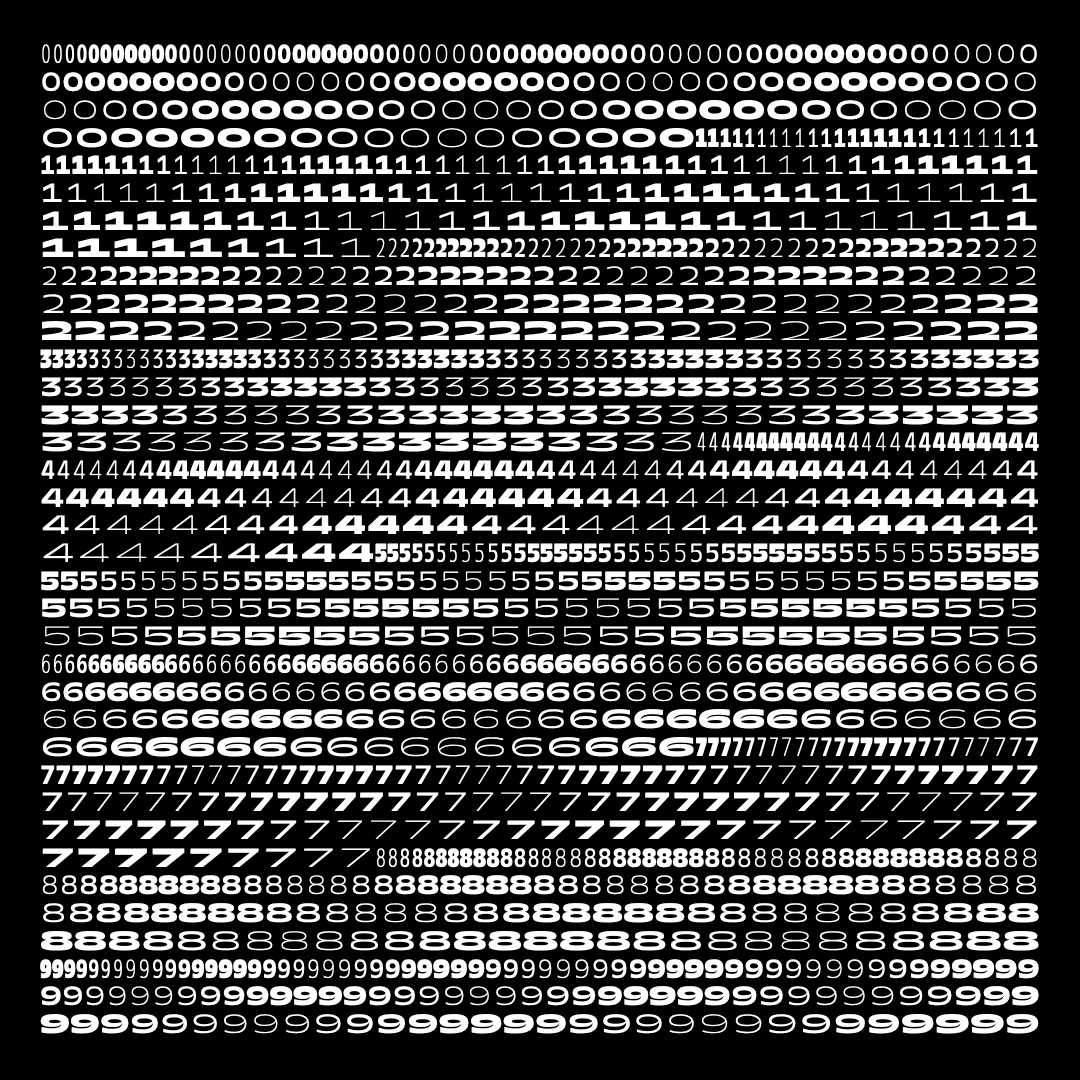
Variable Font: Fließende Anpassungen in einem Absatz; InDesign
ich experimentiere zur Zeit mit variable Fonts in InDesign. Stellt euch dabei folgende Situation vor: Der Absatz des Textes beginnt mit einem schmalen Schriftschnitt. Im Verlauf des Textes fängt die Schrift langsam an immer stärker zu werden, bis sie am Ende der Seite extra-fett wird. Ist es möglich diesen Effekt im InDesign mit variablen Fonts zu erzeugen? Gibt es evtl. ein PlugIn, mit dem man die verschiedenen Zustände des Schriftart fließend im Text ansteuern kann?
hier gibt’s jede menge begabtere grep-spezialisten als mich, aber ich vermute, in dem speziellen fall wird man um viel handarbeit nicht herumkommen.
Ganz allgemein gesprochen: Das ist eher ein Fall für Scripting, nicht für GREP.
GREP: Da praktisch jeder Buchstabe eine Nuance verändert werden soll, müssten erst mal entsprechend viele Zeichenformate angelegt werden, die dann Buchstabe für Buchstabe (automatisch) zugewiesen würden. Das ist immer noch Arbeit, und jede Änderung 1x die selbe Arbeit erneut.
Script in der Theorie
1. Buchstabenzahl in der Markierung / im Absatz ermitteln  (z.B. 500 Zeichen)
2. Minimal- und Maximalwert der variablen Achse des Fonts ermitteln (z.B. von 0 bis 100)
3. Die Anzahl der Buchstaben auf von Minimal- bis Maximalwert verteilen, also die nötige "Schrittweite" ermitteln (z.B: +0,2)
4. Buchstabe für Buchstabe durchgehen lassen, und dabei den Formatierungs-Achsenwert jeweils um eine Schrittweite erhöhen (0,2 0,4 0,6 0,8 1,0 ... 99,6  99,8  100)
In der Praxis ist das keine leichte Nuss zu knacken ...
• zum einen müssen die passenden Befehle für Zeichenzählen und vor allem die Achsenwerte der Fonts gefunden werden, da die recht neu sind ist wahrscheinlich noch wenig vorhanden (im Zweifel: vertiefe dich in der Javascript-Variante der Indesign-Scripts, nicht Applescript oder VBscript – das ist allgemeingültig und soweit ich das sehe besser dokumentiert).
• zum anderen: das Ergebnis könnte gerade bei kurzen Texten ungleichmäßig ansehen, da die Abstufung natürlich nicht völlig fließend ist, sondern eben in Schritten. Wenn dann die Buchstaben verschieden breit sind (ein m ist dann ja doch 4-5x breiter als ein i) bringt das Unregelmäßigkeit rein.
Eine Lösung dafür wäre, die Buchstabenbreite und die "Gesamttextbreite" zu ermitteln und bei der Schrittweite zu berücksichtigen, aber da wirds mathematisch recht komplex  (einfach nur den erst ermittelten Standard-Schritt erhöhen wenn ein m kommt, geht rechnerisch nicht auf, da die Zahl der ms und is (und aller anderen) ja nicht gleichmäßig verteilt ist).
Das verbesserte Script sähe theoretisch so aus:
1. Gesamtextlänge des Absatzes ermitteln (z.B. 10000 pt)
2. Minimal- und Maximalwert der variablen Achse des Fonts ermitteln (z.B. von 0 bis 100)
3. die "Sub"-Schrittweite pro pt Textlänge ermitteln um von Anfang bis Ende von "0" bis "100" zu kommen (statt wie zuvor pro Buchstabe)
4. Buchstabe für Buchstabe durchgehen lassen, und dabei die Breite dieses einen Buchstabens ermitteln, dem entsprechend viele Sub-Schrittweiten für die Anpassung des Buchstabens anwenden und den Formatierungs-Achsenwert jeweils darum erhöhen (m bekommt z.B: 50 Sub-Schritte, ein i bekommt nur 15, ...).
Das sollte ein gleichmäßigeres Ergebnis erzeugen, mit zwei "Kleinigkeiten":
• "Innerhalb" der Buchstaben ist natürlich kein Werte-Verlauf möglich, das gibt die Technik nicht her. D.h. ein "m" ist am Anfang zu dick, und am Ende zu dünn.
• Auch ist die "Gesamttextlänge" nicht ganz einfach ... wenn das ein guter Font ist, kommt Kerning ins Spiel, das verringert in der Regel die Gesamttextlänge, ist dann aber bei der Messung jeder einzelnen Buchstabenbreite nicht mehr so einfach zu berücksichtigen (es geht mit "Vorschau" auf das nächste Zeichen und Ermittlung des Kernings dazwischen, aber da wirds dann endgültig ... schwierig).
vor 54 Minuten schrieb Sebastian Nagel:
Da praktisch jeder Buchstabe eine Nuance verändert werden soll,
Vielleicht würde es @Jo Nas ja fürs Erste auch schon genügen, in Zeilen »zu denken«? Würde das die Sache nicht erheblich vereinfachen und eventuell möglich machen?
vor 9 Minuten schrieb R::bert:
in Zeilen »zu denken«?
Wäre jetzt auch mein Vorschlag gewesen :nicken:
Das könnte ich mir auch in der Erscheinung besser vorstellen, weil der »Verlauf« nur in eine Richtung ginge. Ansonsten hätte man am Zeilenanfang immer einen Bruch, weil dort der Sprung größer ist als in der Zeile – je nachdem wie groß die einzelnen Sprünge und wie lang die Zeilen sind :-?
Gerade in einer Werbung von Sharp:
9d3f62b4-042d-4d13-8a3b-d85fe3f40afd.gif
Da alterniert jedes Zeichen. Aber muss halt nichts berechnet werden (siehe Beitrag von Sebastian), da einfach nacheinander alle fetten durchlaufen.
@Sebastian Nagel Vielen Dank für die ausführliche Antwort. An die Problemstellung des Kernings habe ich noch garnicht gedacht. In Anbetracht der doch sehr komplexen Umsetzung würde ich eher zur "1-Zeilen-Lösung" von @R::bert tendieren.
@Thomas Kunz super Beispiel! Soähnlich habe ich es mir auch vorgestellt. Kennt ihr evtl. ein Code-Beispiel für ein ähnliches Projekt? Gern auch lösgelöst von InDesign, wenn das einfacher ist.
Vielen Dank für die tolle Hilfe!
@R::bert Gute Idee! Ich habe mich mit dem Designer in Verbindung gesetzt. Wenn er die Lösung für das Problem verrät, poste ich es hier in den Feed.
@TobiW die Software war mir völlig neu. Ziemlich spannende Sache. Das könnte funktionieren. Auf youtube habe ich bereits Beispiele gefunden, die in die richtige Richtung gehen.
ein paar Einwürfe (vom Smartphone aus – edit: nachformatiert )
Zeilenweise (also nur von links nach rechts)
das Prinzip bleibt das gleiche (Stufen auf Zahl der Zeichen / Zeilenlänge verteilen). Der visuelle Effekte ist ein anderer.
Aber: wenn das ein durchgängiger Text ist, also das Ende der Zeile nicht manuell umbricht (Prosa statt Vers), dann verändert sich durch die Formatierung die Zeilenlänge, der Text bricht früher um als in normaler Formatierung, und was ganz rechts fett sein sollte steht jetzt links und sollte dünn sein - spannend ;-) das geht mit Rekursionsschleifen bis eine Balance gefunden ist, aber da möchte ich nicht mal anfangen drüber nachzudenken ...
Bei Durchwanderen des ganzen Absatzes wird zwar der Absatz länger, aber die Zeilen beeinflussen sich nicht gegenseitig. Vielleicht ist das also sogar die einfachere Übung.
Sharp-Beispiel
da haben wir die Vereinfachung, dass die Zahl der Zeichen fixiert ist, die Zahl der Fettgrade fix ist, und dann nur Zeichen für Zeichen das Gewicht erhöht und wieder vermindert wird. In zeitlicher Rotation ergibt das dann den Welleneffekt.
Die Ermittlung der Zeichenzahl / Textlänge fällt weg, und wir müssen keine Variable-Font-Parameter verändern. Wenn das Variieren in feinen Abstufungen  der Sinn der Übung war, geht das so natürlich etwas am Ziel vorbei.
Drawbot, Browser oder InDesign?
im Grunde bleibt die Logik dahinter die selbe. Was sich verändert ist die Programmiersprache (Javascript, Python) und die Objekte die angesprochenen werden können/müssen (Indesigns spezifische Objektdefinition/Funktionen in JS, normales Browser-DOM/Javascript, oder - vermutlich - eine Objektauswahl/Funktionen die Drawbot spezifisch anbietet). Das kann dann im einen oder anderen Tool mehr oder weniger komfortabel oder intuitiv sein (Browser vermutlich am wenigsten, Drawbot möglicherweise am einfachsten), aber vermutlich wäre es in allen Umgebungen lösbar und von hier zu da übersetzbar, wenn erst mal die unabhängige Grundlogik funktioniert.
Bleibt auch die Frage, für was man das ganze am Ende braucht - ein Ausdruck, eine Webseite (Animation?), ...
vor 2 Minuten schrieb R::bert:
von oben nach unten
Aber da hast du prinzipiell ein ähnliches Problem, oder? Wenn der Text einfach so (ohne manuelle Zeilen- oder Absatzumbrüche) durch den Textrahmen fließt, musst du irgendwie heraus bekommen, an welchem Zeichen der Text automatisch umgebrochen wird, weil sich dort dann ja die Formatierung ändert. Aber durch diese Änderung ändern sich dann auch wieder die Umbrüche. Sicher irgendwie machbar, aber nicht trivial. Da fände ich es sehr viel geradliniger, einfach den ganzen Text Zeichen für Zeichen durchzugehen und eben bei jedem Zeichen ein bisschen am Achsenwert zu drehen.
(Weil ich ID jetzt nicht wirklich kenne, denke ich jetzt nur in Javascript im Browser.)
vor einer Stunde schrieb R::bert:
Gut, ich bin von oben nach unten ausgegangen …
Bei "von oben nach unten" haben wir – denke ich – das selbe Problem ... die Zeilen werden durch die Formatierung immer länger, müssen (wenn fixe Satzbreite) umbrechen und sollten dann eigentlich schon wieder anders formatiert sein als sie in der ersten Iteration formatiert wurden – letztlich arbeiten wir in diesen beiden Fällen in zwei Dimensionen, während wir uns beim Durcharbeiten des gesamten Absatzes  eigentlich linear bewegen. Es ist alles "eine Textwurst", die erst danach vom Satzprogramm automatisch ungebrochen wird, aber das kann dem Script egal sein.
vor einer Stunde schrieb Þorsten:
(Weil ich ID jetzt nicht wirklich kenne, denke ich jetzt nur in Javascript im Browser.)
Im Grunde ist das exakt gleich.
Man hat nur in Indesign zusätzliche Objekte und Funktionen zur Verfügung, die spezifisch für Indesign-Inhalte sind. D.h. alles was in Indesign ein Objekt ist (Font, Glyphe, Absatz, Zeile (hoffentlich!), Zeichen, ...) und alle Indesign-Eigenschaften von Objekten (Formatierung, Dimension (hoffentlich!), Position, ...), und alle Funktionen die Insign anbietet (Format verändern, ...) kann angesprochen und verwendet werden.
Und natürlich stehen alle Standard-Funktionen von Javascript zur Verfügung (Variablen, Schleifen, Logik, Stringfunktionen, ... ...). Was möglicherweise nicht implementiert ist oder fehlt sind Sachen mit Server-Kommunikation, etc. die halt netzwerk- und nicht dokument-spezifisch sind.